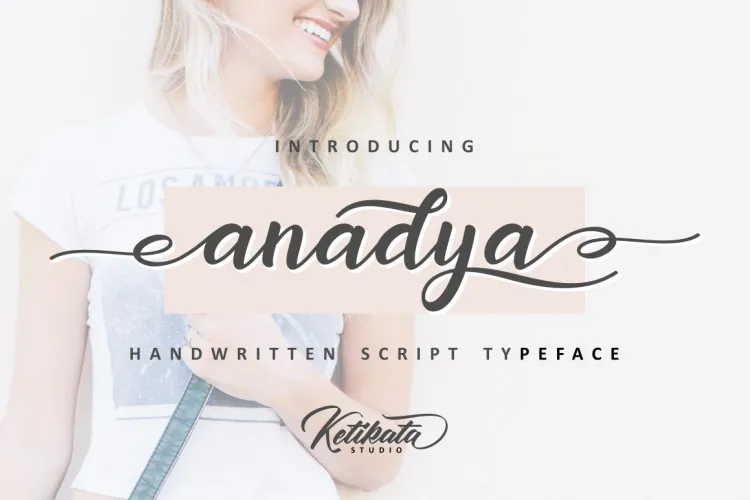
Anadya Handwritten Script Font – Download Grátis
Anadya Handwritten Script Font é uma opção moderna para designers que desejam adicionar um toque elegante a suas criações digitais. Inspirada na escrita à mão, esta font se destaca por sua sofisticação e originalidade. Ideal para aplicar em designs de gráficos delicados ou outros projetos como cartões de visita, materiais de merchandising e embalagens, Anadya oferece uma variedade de alternativas estilísticas e curvas fluidas que permitem personalização extensiva. Esse é um font cuidadosamente concebido para quem busca expressar elegância e delicadeza em seus trabalhos. As alternativas estilizadas permitem criar designs únicos e sofisticados, perfeitos tanto para design de moda quanto para outros segmentos como publicidade ou identidades corporativas. Anadya é uma escolha inteligente se você está buscando personalizar seu projeto com um touch elegante e único, seja na criação de slogans, em cartões de visitas, embalagens chamativas ou qualquer outro tipo de trabalho gráfico.